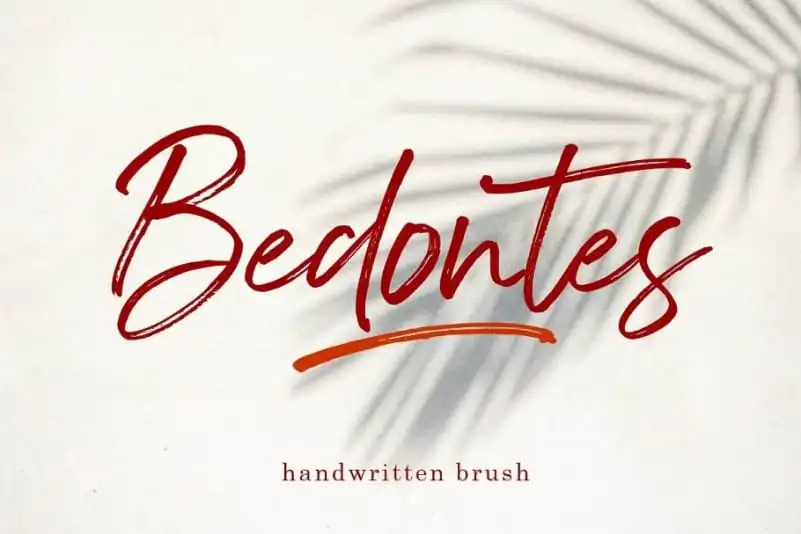
Através do designer 99designs surge Bedontes Brush Font, uma elegante tipografia script que transborda naturalidade e graça. Inspirada na arte de traçar com um pincel, esta fonte apresenta linhas ágeis e distintas, criando um contraste notável entre os traços finos e espessos. Através do processo de desenho, escaneamento e vetorização, Bedontes Brush Font transpassou a tinta da folha para o vidro digital, resultando numa obra que se destaca por sua vivacidade e beleza. Este tipo especializado no estilo script é ideal para enriquecer qualquer projeto design, seja ele para fins publicitários ou gráficos artísticos. Descubra a riqueza de detalhes e alegria contida nesta fonte única.